去年11月,英国知名创意资讯平台Creative Boom发布了一份字体趋势预测,汇集了2020年度可能受设计师欢迎的20款英文字体,其中Helvetica Now众望所归拿下第一。
今天,Creative Boom于官网正式公布了2021年度最受欢迎的字体趋势预测,共有24款字体上榜。其中包括:6款Sans Serif fonts(无衬线字体)、4款Slab Serif fonts(粗衬线字体)、8款Serif fonts(衬线字体)以及6款Display fonts(标题字体)。
无衬线字体
1. Anguita Sans
由设计师Sofia Mohr设计的Anguita Sans是一款较窄字宽的无衬线字体家族,共包含8种字重及包含斜体的16种样式。
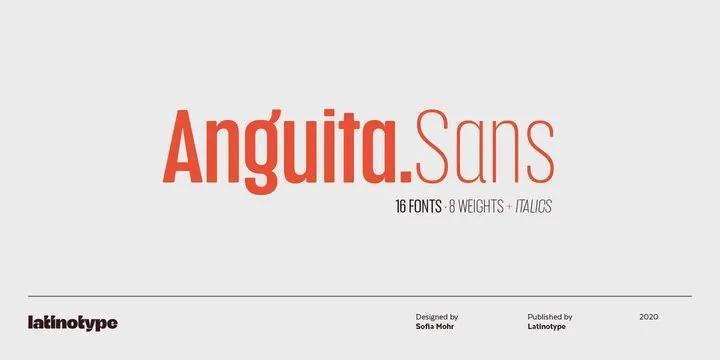
于今年10月5日首次亮相,字体的特征是边缘的圆角和较大的x字高以及紧凑的字型结构,是一种时尚且用途广泛的字体,非常适合广泛的应用,特别是应用于印刷和数字媒体中的标题和正文。
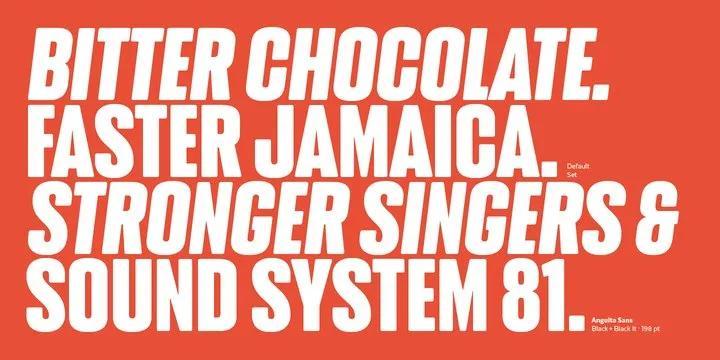
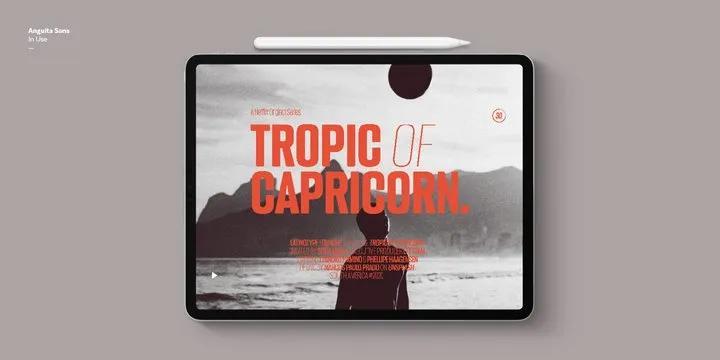
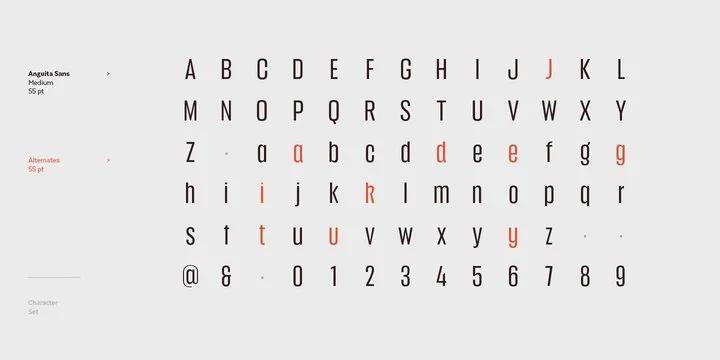
2. Jeko
Jeko是一款由设计师llen Luff基于Aventa重新设计的新几何无衬线体,于今年9月正式推出。
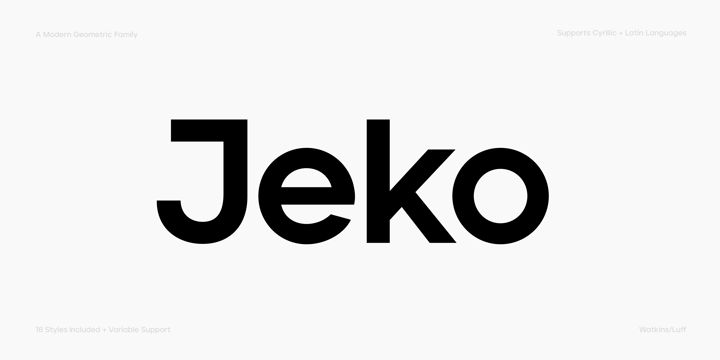
由极简的几何形状和干净的圆圈组成,并且已被制作为最新的可变字体格式,每个字体包含超过570个字形与完整的西文、中欧、东欧和西里尔语言支持。
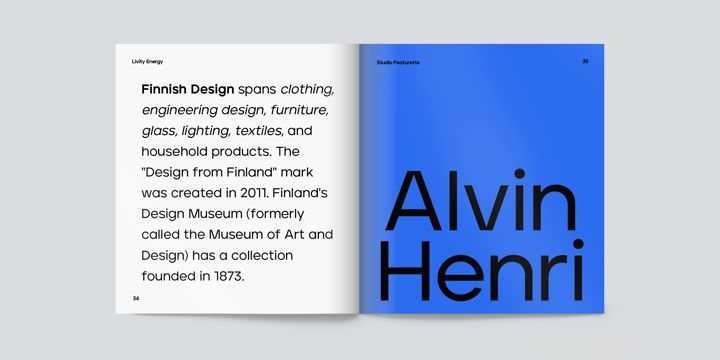
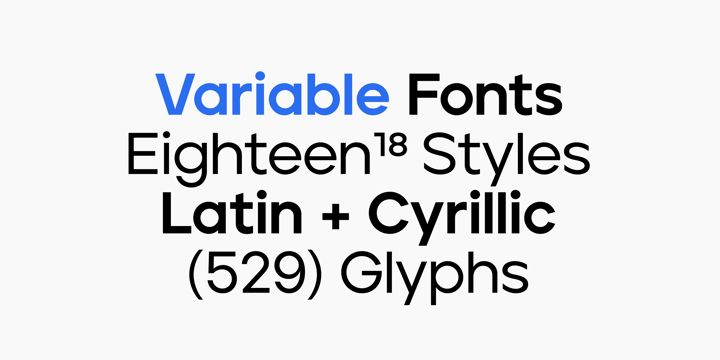
3. Goldplay
由EnriqueHernández为Latinotype设计的Goldplay是基于IsidoraSans的一个进化版。
于去年10月推出,其清新的现代风格和经典比例的组合使其成为标题、标志、书籍、杂志和运动图形的极佳选择。
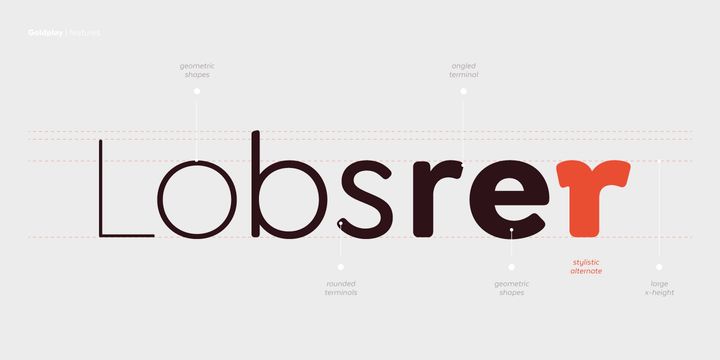
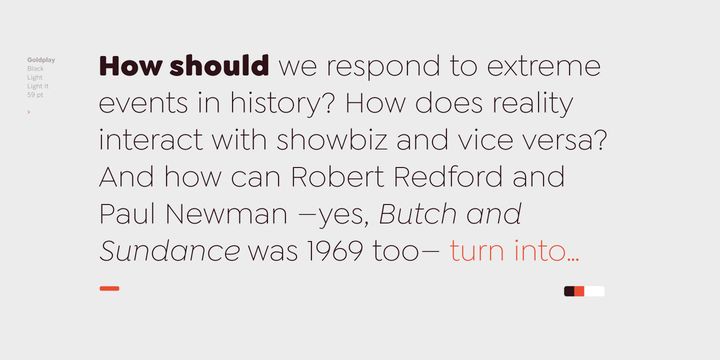
4. Versus
由设计师Marcelo Moya Ochoa设计的Versus是一款用于短文本和块状文本的字体。该字体基于拳击海报上常见的字体,结合了拉丁美洲的元素和摔跤元素。正是这种宽度和重量以及不同风格的结合,有助于使你的设计具有独特的风格和个性。
Versus系列共有9种字重,从极细的Extra Light到极粗的Ultra,它的字符集支持200多种不同的语言。字体还包括大量的风格替代品和完整的连字集,使你的作品具有强烈的个性。
5. Olivetta
由设计师AlfonsoGarcía设计的Olivetta将单词的力量展示为图像。小写字母的粗笔和细笔之间的高对比度使字体具有强烈的视觉冲击力。
Olivetta共包含10种字重,带有匹配的斜体,每种样式都包含400多种字形,其中包括替代字形。
6. Trust Sans
Trust Sans是一款专门为企业形象设计的字体。这款字体于去年10月推出,由设计师Antonio Mejía为墨西哥拉丁字体设计,具有柔和的流畅和人性化的特点。
Trust Sans由2个互补的子家族组成:一个标准的正式字体和另一个更随意的版本。每个系列有包含6种字重,并带有匹配的斜体,家庭字形集支持超过200种基于拉丁语的语言。
原标题:字体趋势:2021年将流行的24款字体